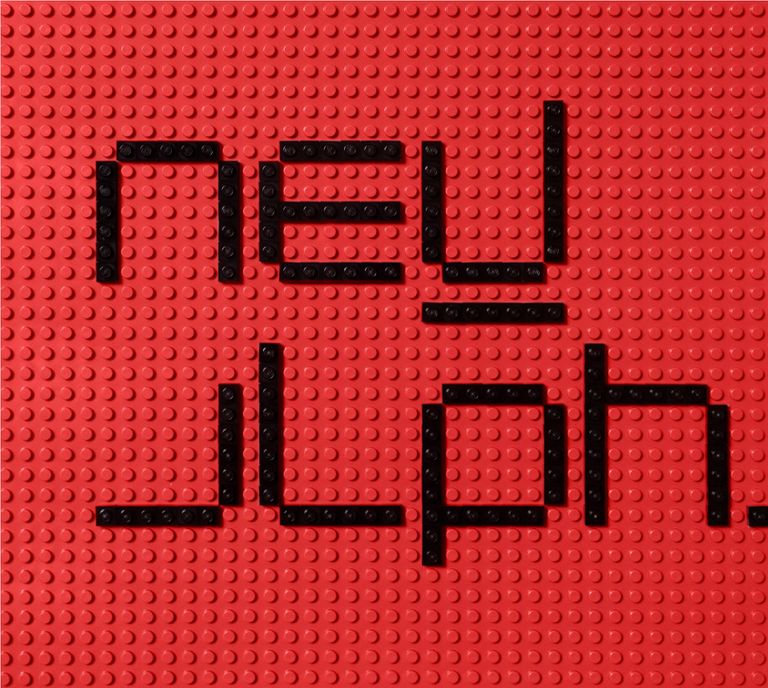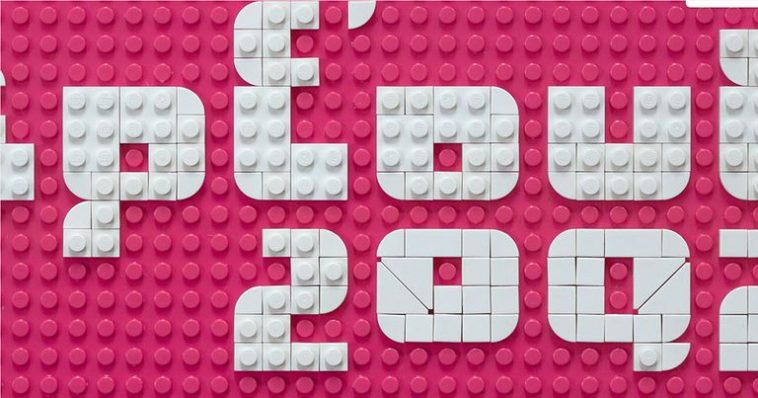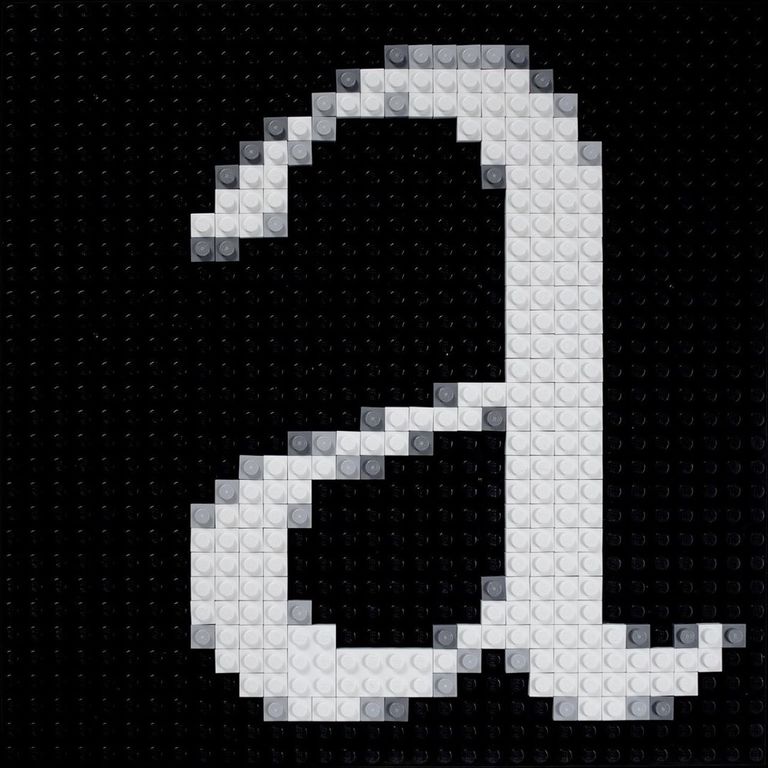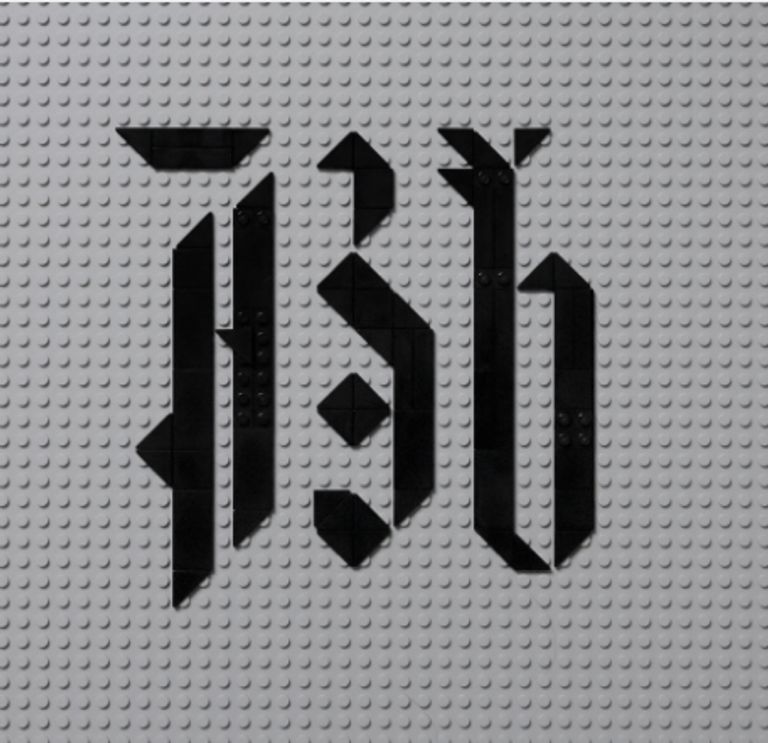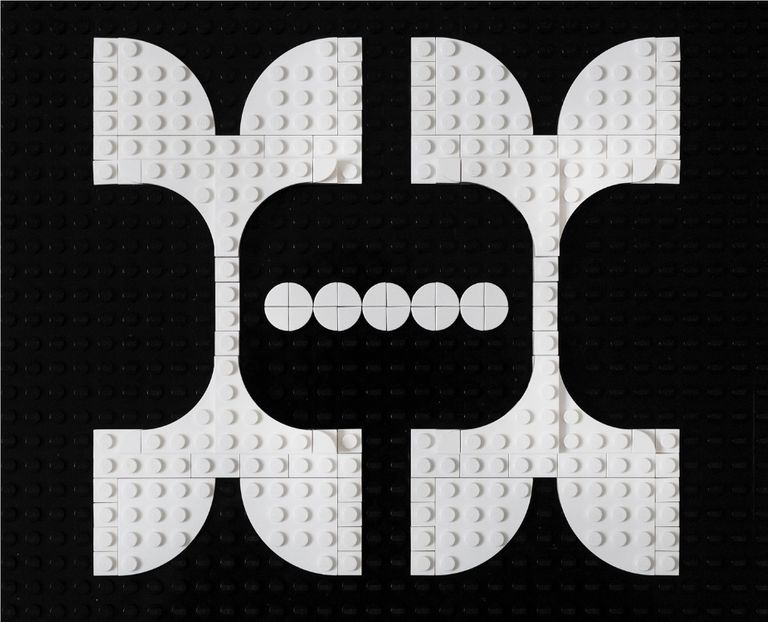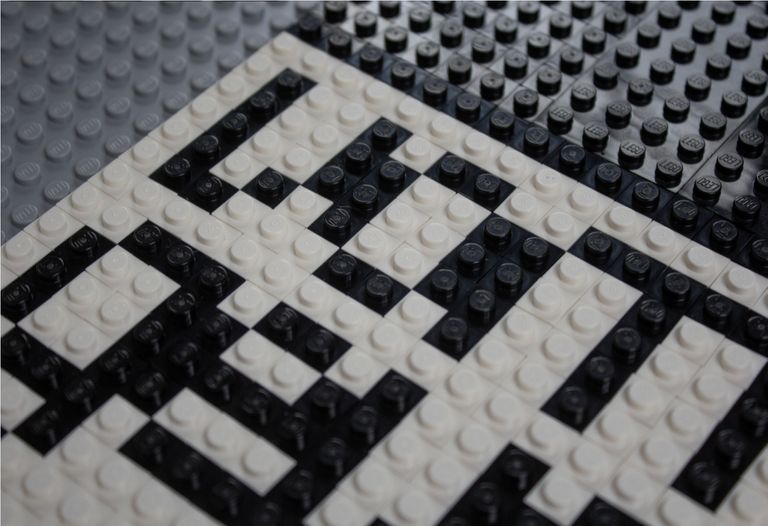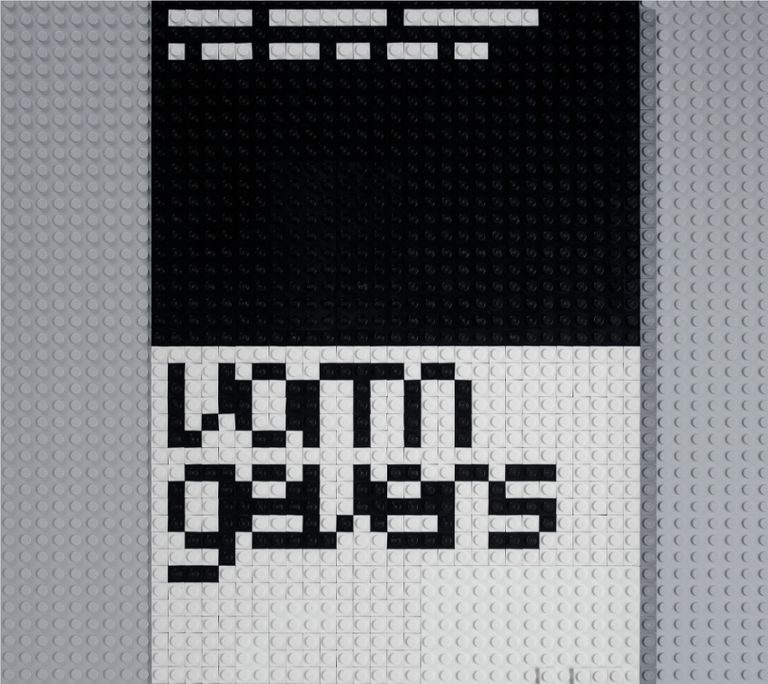
ლეგოებით თითქმის ყველაფრის აშენება შეგვიძლია. სწორედ ამიტომ, პატარა პლასტმასის ფიგურები ყველასთვის მიმზიდველია. დიზაინერმა კრეიგ უორდმა კი, Brik Font, ანუ ლეგოების ფონტი, შექმნა. დიახ, ასოები ლეგოს ფიგურებისგან, მისთვის დამახასიათებელი სტილით დაამზადა. ფონტის ყველა ასო საგულდაგულოდ არის შექმნილი, მასშტაბირება კი კომპიუტერის ეკრანზე, ან შესაძლო რეტრო ვიდეოთამაშზეა შესაძლებელი. ბლოგერმა ჯეისონ კოტკემ კი აჩვენა, თუ როგორ გამოიყურება შრიფტი ახლოდან, Photoshop-ში მუშაობისას.
კრეიგ უორდის პროექტის ინსტაგრამ გვერდზე ხშირად შეხვდებით რაღაც ნაცნობს, ბაუჰაუსიდან გარამონდამდე. Brik Font კი ლეგოს ხელოვნების ნიმუშად მიიჩნევა. აქ ასოების გარდა, ისრების მსგავს სიმბოლოებსაც შეხვდებით.
ამბობენ, რომ სრულყოფილების ძიება დაუსრულებელი სწრაფვაა, მაგრამ იმის დანახვა, თუ როგორ იქმნება ასო O მართკუთხა აგურებიდან და როგორ ჯდება ყველა ფიგურა ერთმანეთში, სრულყოფილების შეგრძნებასთან ძალიან ახლოს დგას.